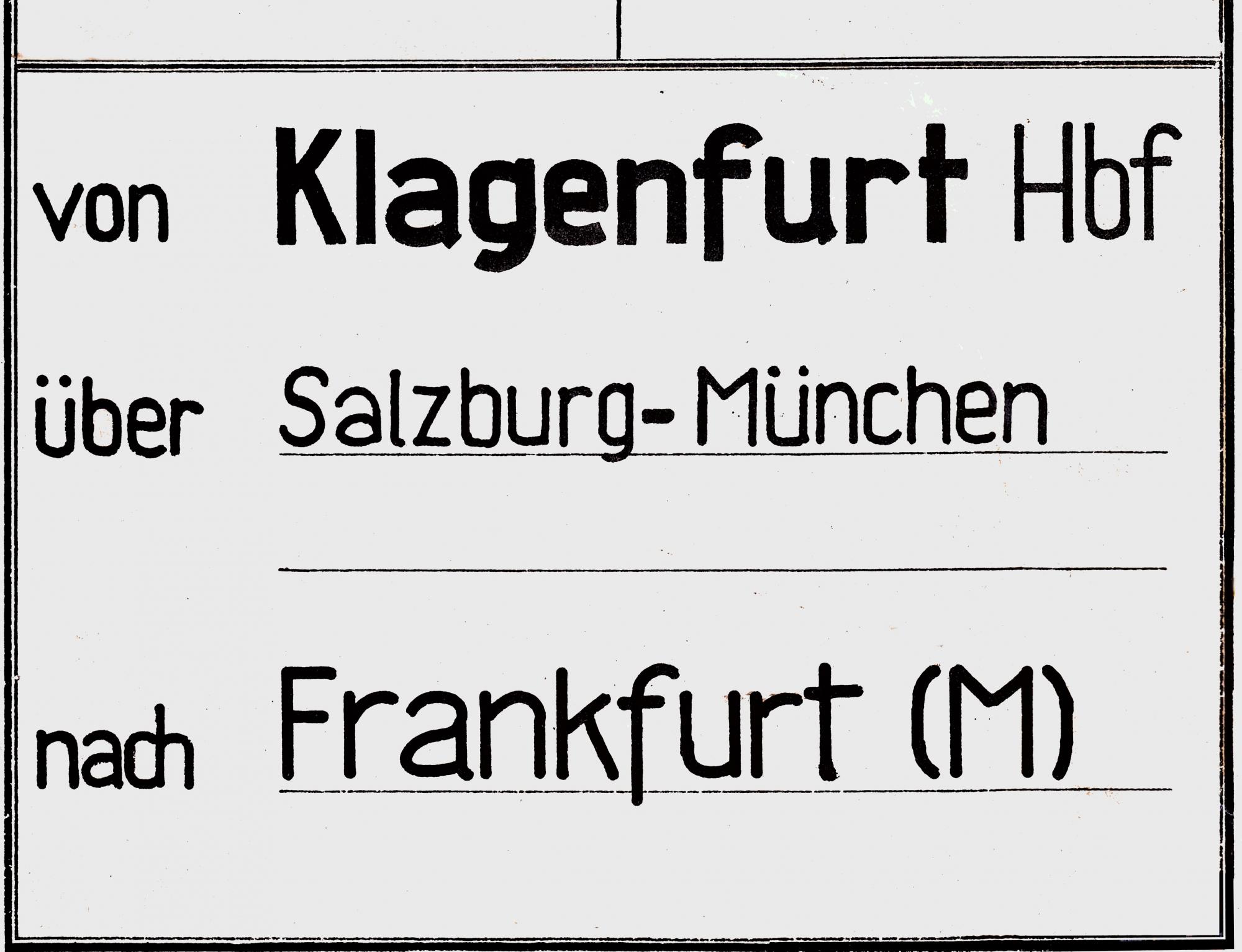
[Mitglied FdE…] Geschrieben August 28, 2020 Teilen Geschrieben August 28, 2020 Hallo und Guten Tag Mein Hobby ist Eisenbahn, ich suche die, wahrscheinlich Schablonierschrift auf diesem Laufzettel eines Zuglaufes. Die Schrift ist auf auf einem Schild für Platzreservierungen. Es geht um die Schrift der Stationsnamen. Die vorgedruckten Feldnamen von - über - nach , kenne ich , es ist DIN 1451 Engschrift. Aber besonders das M ist auffällig. Welche Schrift könnte das sein? Danke für ihr Interesse. Gruß Franz A. Keck Link zu diesem Kommentar
[Mitglied 3098…] Geschrieben August 28, 2020 Teilen Geschrieben August 28, 2020 Das ist alles handgeschrieben, man wird also höchstens eine ähnliche finden. Link zu diesem Kommentar
Beste Antwort [Mitglied Erwi…] Geschrieben August 28, 2020 Beste Antwort Teilen Geschrieben August 28, 2020 Die Schrift wurde mit einer Schriftschablone gezeichnet. Nicht besonders genau, deshalb das unschöne "M". Diese Schablonen sind auch heute noch im Handel erhältlich. Link zu diesem Kommentar
[Mitglied FdE…] Geschrieben Mai 13, 2021 Themen-Ersteller Teilen Geschrieben Mai 13, 2021 Hallo bertel und Erwin Aufgrund persönlicher Umstände bin ich erst heute in der Lage, mich für Eure Antworten zu bedanken. Ich habe mir fast schon gedacht, dass dies keine gedruckte Schrift ist. Link zu diesem Kommentar
[Mitglied catf…] Geschrieben Mai 13, 2021 Teilen Geschrieben Mai 13, 2021 Und wenn es dann auch eine sauberere Schablonenschrift sein darf, hätte ich die: http://www.peter-wiegel.de/TGL_0-16.html 1 Link zu diesem Kommentar